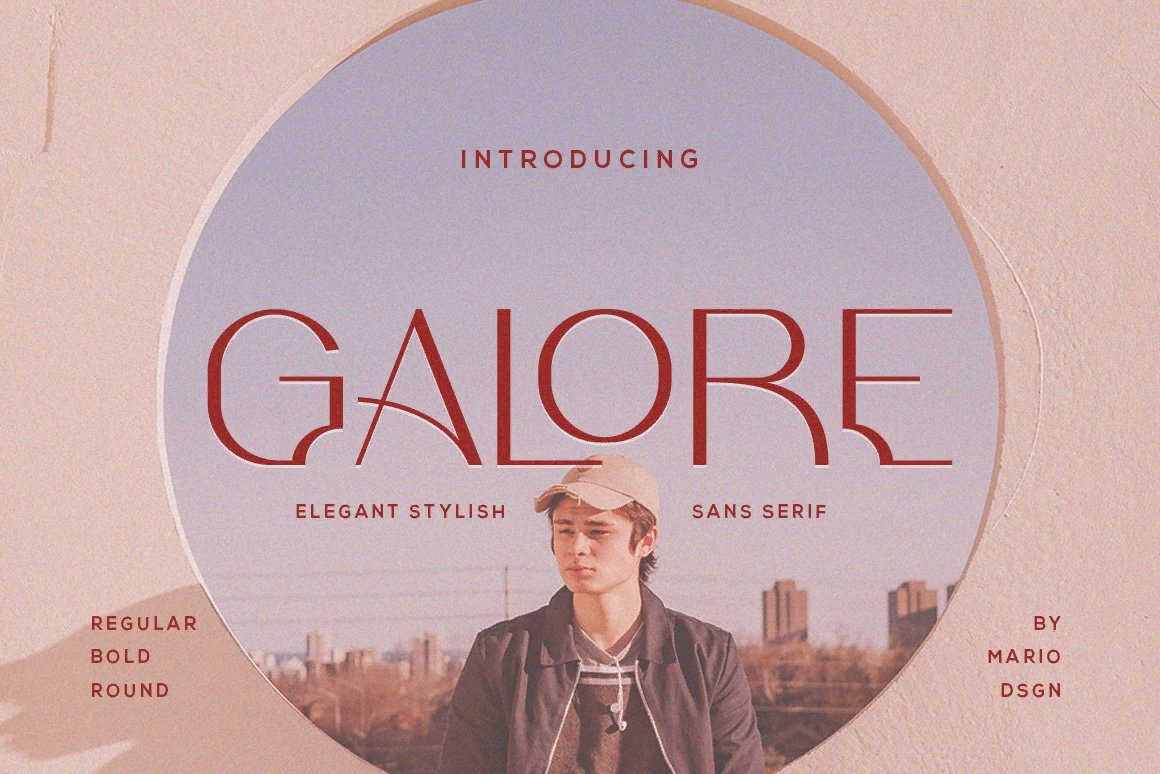
Название: Galore Font (2021)
Galore - элегантный, тонкий и современный шрифт без засечек.
Этот нежный шрифт будет великолепно смотреться на различных дизайнерских идеях.
Он добавит романтическую нотку в каждый ваш проект!